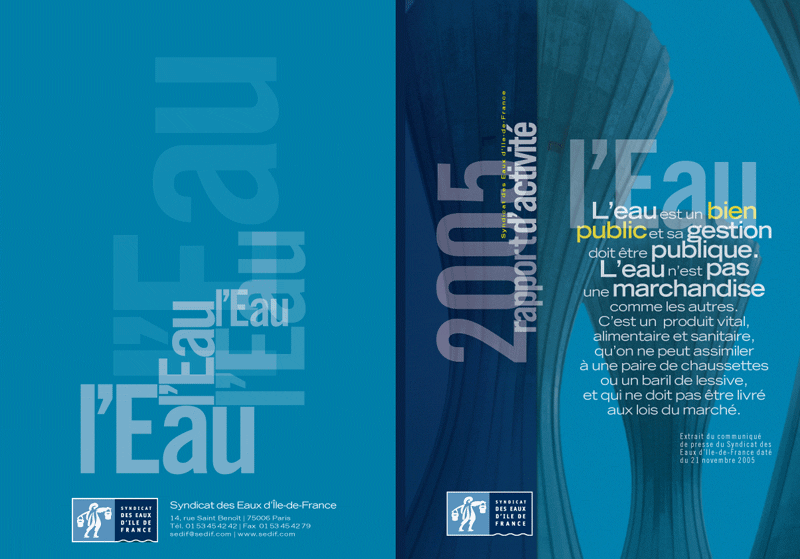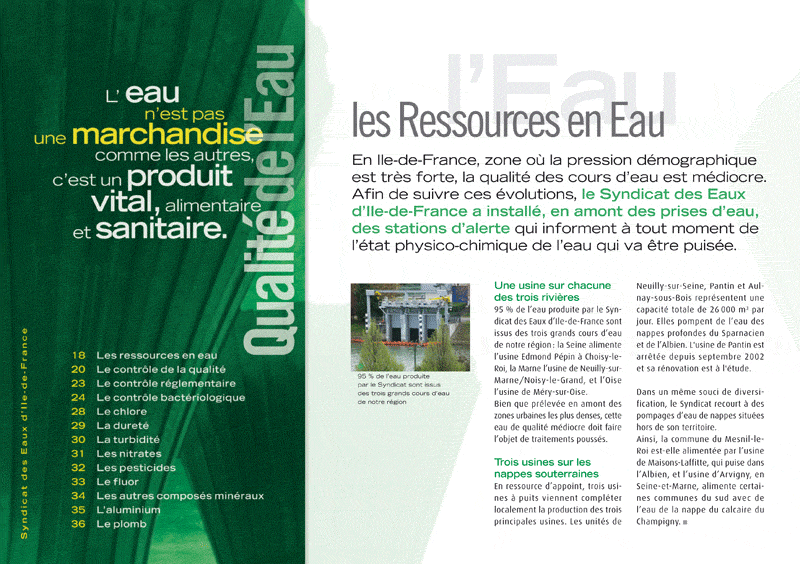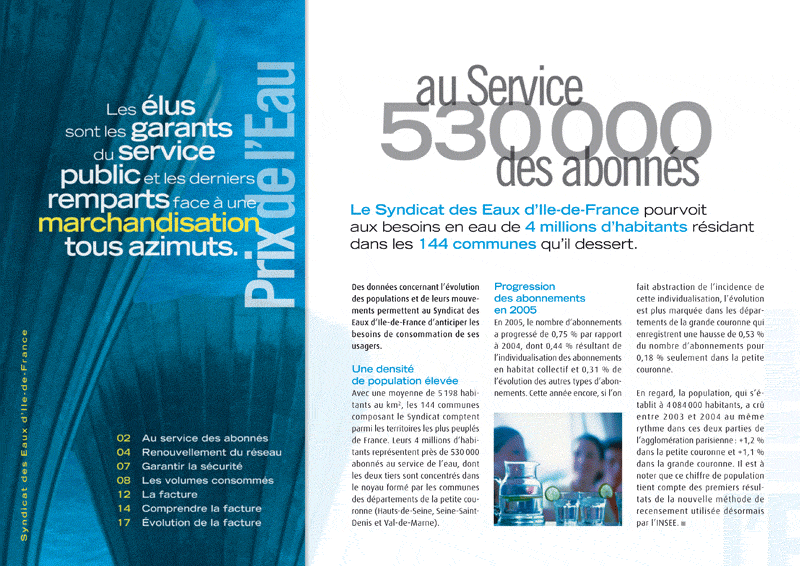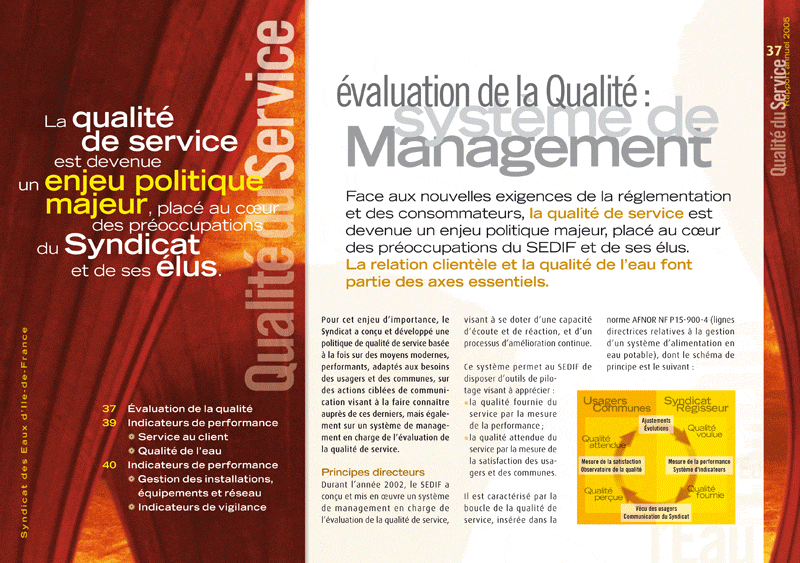
En 2006 une agence m’a contacté pour assurer la direction artistique du rapport annuel de la Sedif (Syndicat des Eaux de l’Ile de France). Il s’agissait pas de n’importe quelle demande et de n’importe quel objectif. L’institution est en proie à des attaques régulières par des lobbyes privées qui veulent s’emparer de cette manne financière. L’eau coule si facilement. Vincent Rode, le consultant de l’Agence Graphitit a fait passer le message auprès de la Sedif. «Cette fois on va utiliser un style rédactionnel fort pour faire passer le message» Et quoi de plus naturel que de faire appel à un typographe militant qui croit en les vertus sacrés de l’alphabet de 26 lettres pour faire passer l’engagement politique ou sociale.
Évidemment dès lors que l’on ne fait plus appel au même typographe pour réaliser le site web, cela donne ceci … un espace visuel à peine tendance, qui ne dégage plus rien de la théatralisation des messages engagés. Edulcoré, soporifique, et sans l’odeur de l’encre (virtuel) militant. Le site revient vers le monde du consumérisme moderne… Qu’on ne s’étonne plus après des ratages de la communication globale. Qu’en pensez-vous?